喜歡收集不同的字體嗎?各位機會來啦!小編最近發現 Mega Font Bundle 上,推出 211 款英文字體,原價 3,354 美金,換算台幣價值超過 10 萬元,最重要的是通通「終身」免費商業使用,各式風格的英文字體都有,不論是可愛英文字體、手寫英文字體、設計英文字體等,各位趕快下載起來吧,馬上幫你省 10 萬。小編再加碼推薦免費英文字體下載網站 Fontshare,50 種英文字型,可個人及商業用途免費使用。
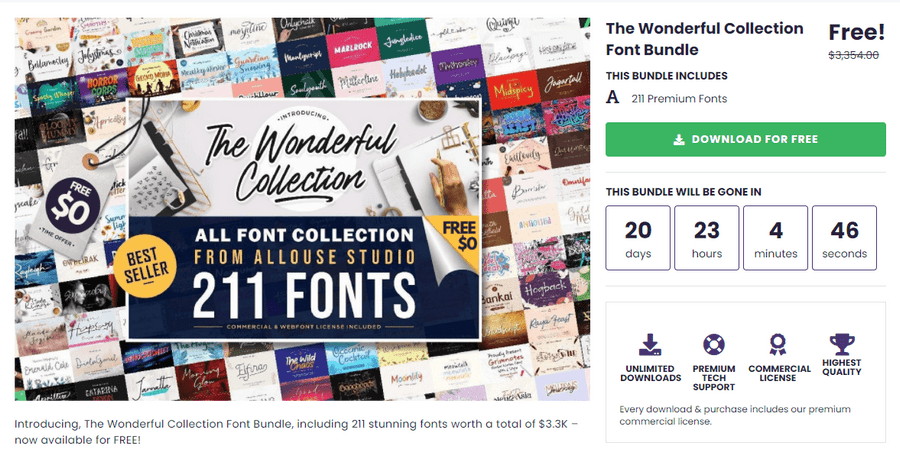
再往下滑一點,就能夠看到本次 211 款英文字型的呈現效果、字體名稱、作者及字體價格。